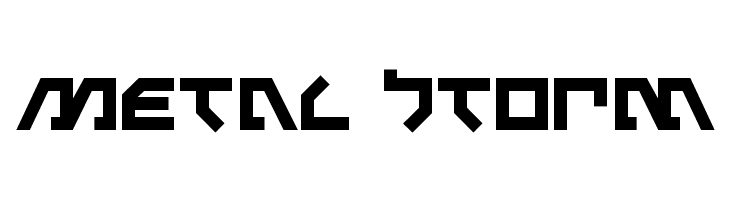
A playful and artistic font featuring hand-drawn animal faces.
A clean, modern sans-serif font with consistent stroke width and balanced spacing.
A playful, hand-drawn font with tall, narrow characters and a whimsical style.
An elegant, italic script font with a calligraphic style.
A bold, dynamic handwritten font with flowing strokes and playful bounce.
A bold, graffiti-inspired font with dynamic, expressive strokes.
A high-contrast, elegant serif font with a modern yet classic appeal.
An elegant, flowing script font with a classic calligraphic style.
A bold, handwritten-style font with high contrast and expressive character.
A modern, light sans-serif font with clean lines and consistent spacing.
A lively, expressive handwritten font with fluid, dynamic strokes.
A bold, angular font with a geometric and impactful style.
Playful handwritten font.
A bold, geometric font with a three-dimensional, angular design.
A bold, 3D font with a modern, geometric design and shadow effects.
A whimsical and playful font with looping and swirling strokes.
A playful, handwritten font with bold, rounded strokes and a casual, friendly appearance.
A bold, italicized font with a gradient effect and dynamic, modern style.
A modern, extra condensed, semi-bold font with clean lines and geometric shapes.
A futuristic, bold font with rounded edges and a geometric design.
A bold, rounded font with a modern and playful style.
A modern serif font with elegant, elongated characters and balanced serifs.
A bold, expressive script font with a flowing, handwritten style.
A bold, rugged font with distressed edges and a hand-crafted appearance.
A modern, elegant script font with a slight slant and fluid, connected characters.
A bold, decorative font with a layered, geometric design.
An elegant, flowing script font with a natural handwriting style.
An elegant script font with ornate swirls and flowing, interconnected letters.
A modern, geometric sans-serif font with clean lines and balanced structure.
A hollow, geometric font with a modern and minimalist design.
A bold, distressed font with a rugged, grunge-like appearance.
A playful collection of heart-themed doodles with a whimsical, hand-drawn style.
A bold, playful font with a graffiti-inspired style.
A bold, handwritten font with a playful and energetic style.